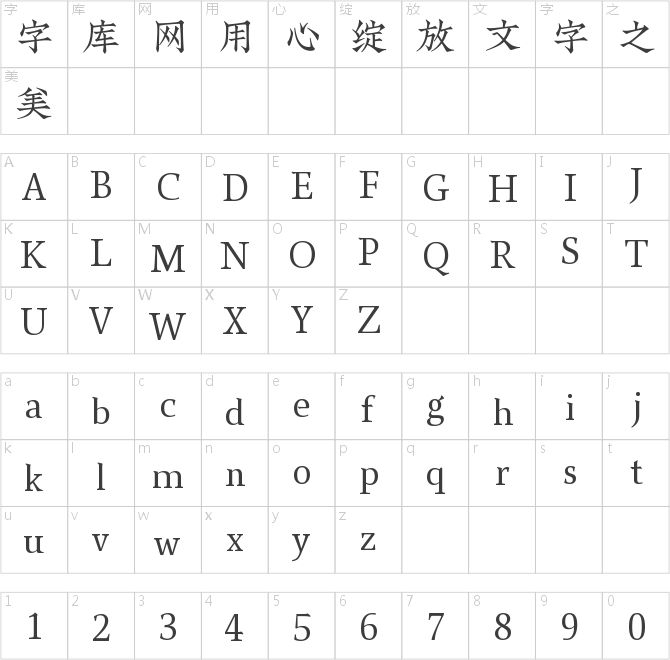
字體名稱: 喜鵲聚珍體
喜鵲聚珍體
喜鵲聚珍體是汲取20世紀初期丁氏兄弟所創(chuàng)聚珍仿宋風格,復刻而成的簡體字庫,于2018年7月26日正式發(fā)售。
喜鵲聚珍體字體字庫是一款讓人賞心悅目、百看不厭的中文字體,適合各類廣告和產品包裝設計應用,字體大小5.18MB,格式為ttf字體,上傳用戶是瀨子,作者/版權方為喜鵲造字